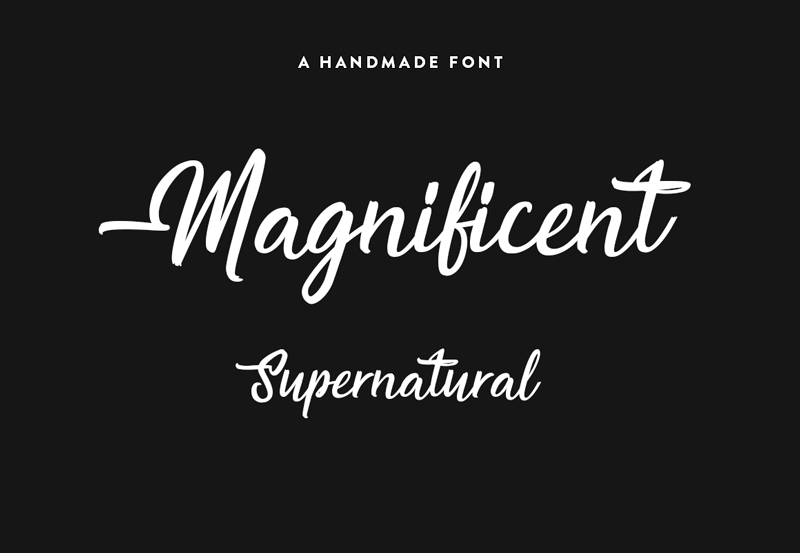
Magnificent Supernatural Font – Download Grátis
A Magnificent Supernatural Font é uma fonte escrita à mão que oferece uma sensação mágica e encantadora para qualquer projeto. Criada pelo designer Octotype, essa fonte é perfeita para aqueles que buscam um toque especial em suas criações digitais. Com sua característica estilo livre e natural, a Magnificent Supernatural Font combina elementos únicos com uma elegância sofisticada, tornando-a ideal para qualquer aplicação que exija um ar de misterioso encanto. Seja ela o título de um livro, o design de um logotipo ou até mesmo o texto de uma mensagem personalizada, a Magnificent Supernatural Font adicionará seu próprio toque místico ao projeto. As opções de tamanho e espessura oferecidas permitem aos designers ajustar com precisão, tornando-a perfeita para uma ampla gama de aplicações digitais. Sua disponibilidade em formato completo e licença comercial a torna um recurso imprescindível para qualquer designer que procura incorporar nuances de arte livre na sua próxima criação.